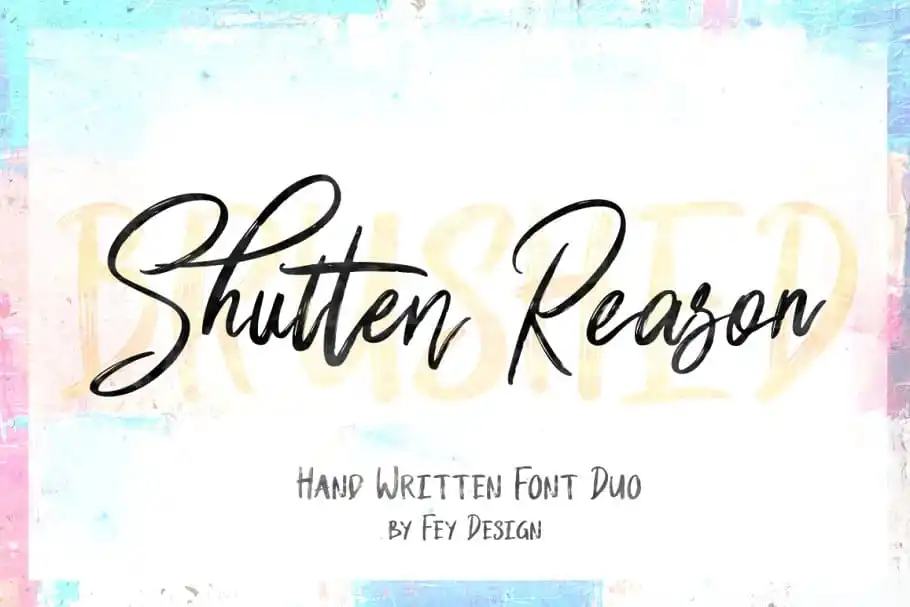
Shutten Reason Font Duo – Download Grátis
A Shuten Reason é uma nova pausa para os amantes do tipo tipográfico. Desenvolvida por Hamilton, essa fonte script dual permite um toque autêntico e artesanal a qualquer projeto, seja ele para design gráfico profissional ou aplicação mais informal. Com seu estilo de letra à mão e sem serif, esta font é perfeita tanto para criações de elementos e logotipos quanto para estampas de camisetas e selinhos em eventos especiais. Seja você um designer, ilustrador ou mesmo alguém que simplesmente adora transformar palavras em arte, Shuten Reason fornecerá o estilo necessário. Suave e fluido, este tipo é uma ótima escolha para aquelas criações em que você quer manter uma pegada mais natural e elegante. É perfeito tanto para os eventos mais formais quanto para momentos descontraídos, tornando-o um recurso gráfico inegável. Não importa o projeto ao qual você deseja dar vida com sua letra: Shuten Reason pode transformar tudo em algo único e inspirador.